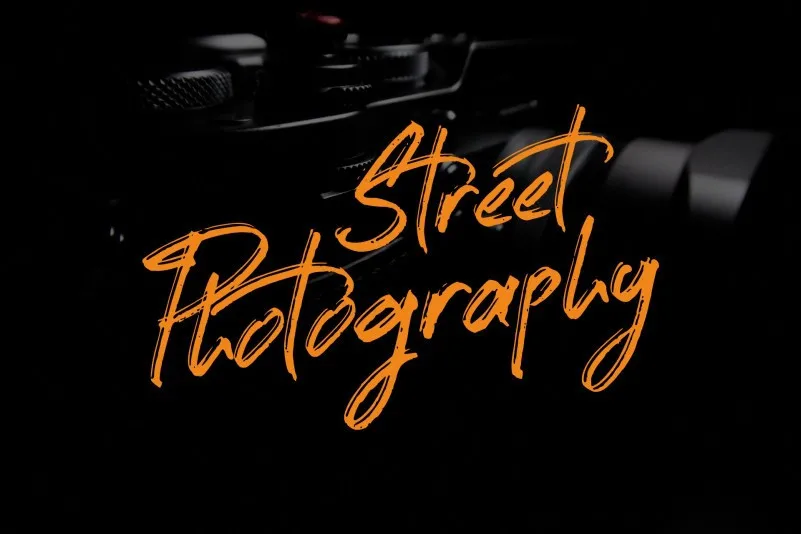
Street Photography Brush Font – Download Grátis
Introduzimos Street Photography Brush Font. É uma fonte feita à mão que combina curvas atraentes com um toque urbano e moderno para criar um estiloso script que garante adicionar uma pegada atraente aos seus projetos. Esta tipografia é criada e compartilhada pela Willetter Studio. Como designer, Tommy Soft trouxe uma qualidade única à Street Photography Brush Font. Suas curvas fluidas e linhas delicadas se encaixam perfeitamente em designs de street photography ou qualquer projeto que explora a atmosfera urbana. Esta fonte é especialmente adequada para criar designs profissionais com um toque autêntico, adicionando uma identidade única a qualquer projeto gráfico. Com seu design cuidadosamente pensado e compartilhado pela Willetter Studio, Street Photography Brush Font é a escolha perfeita para aqueles que desejam trazer um pouco mais de personalização à sua arte digital.